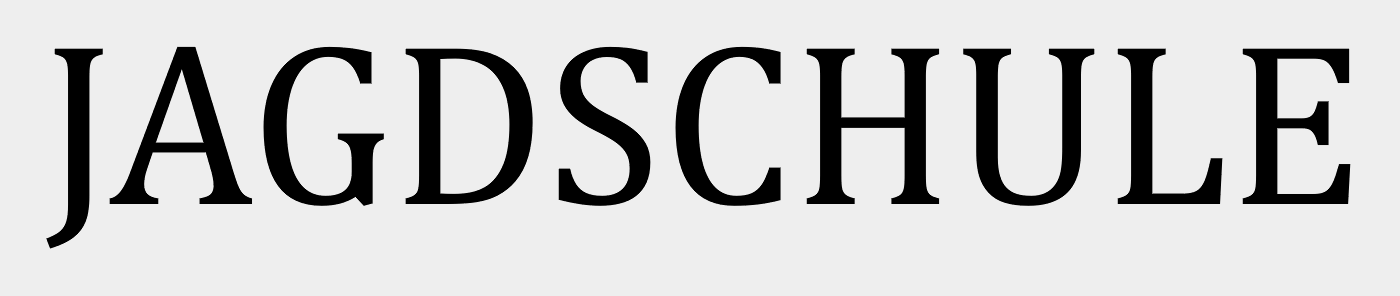
Suche für eine Jagdschule den Font-Namen
Wir haben ein älteres Bildlogo für eine Jagdschule vorliegen und wie so oft liegt dem ehemaligen Designer keine Originaldatei oder die Info zur damals verwendeten Schriftart vor. *hhhmpf*
Bisher wurden wir deshalb leider nicht wirklich fündig und hoffen daher auf Euch.
Bei dem Schriftzug handelt es sich um ein Logo der Jagdschule Schwiessel inkl. Subtext.
Die Grafik ist sehr klein und sehr schlecht, eine Erkennung über Generatoren schwierig.
Unsere erste Wahl bei der ersten Zeile war: "TARSUS MEDIUM". Diese passt zwar nicht 100% wäre aber in Ordnung.
Kniffliger ist die zweite Zeile.
Habt Ihr da Ideen, welche Schriftart das sein könnte? Markant sind vor allem die Großbuchstaben was die Auswahl einer alternativen Schriftart schwierig macht.